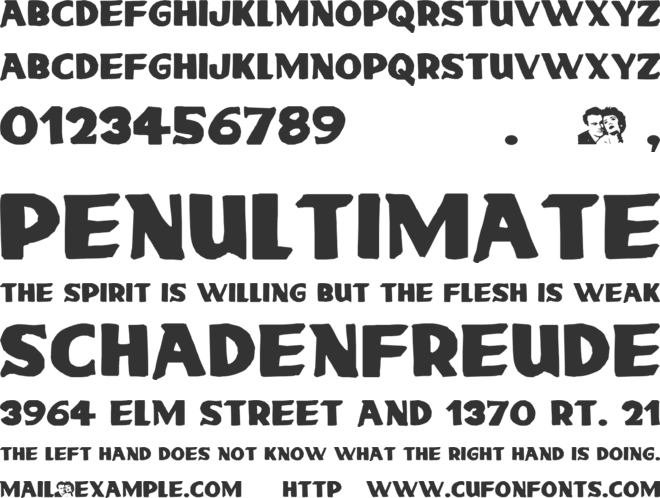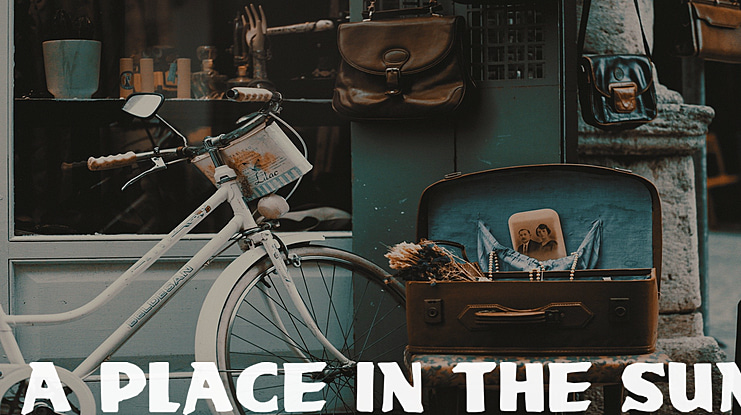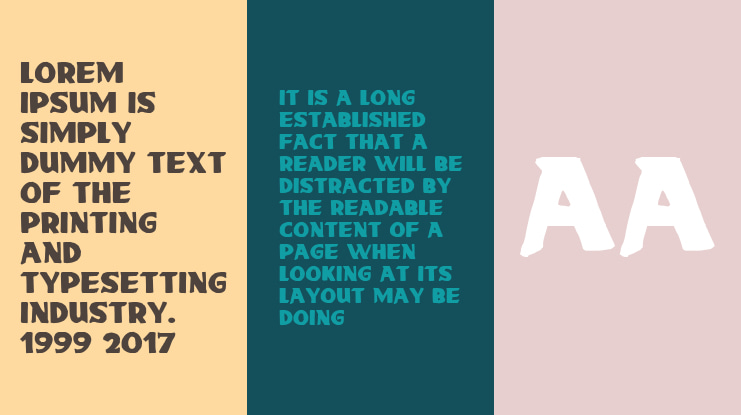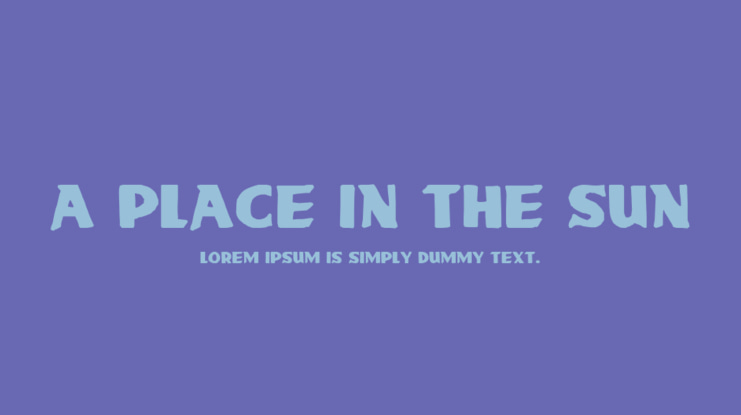
A place in the Sun Font
P.A.Vannucci
Direttamente dal film diretto da George Stevens e interpretato da Montgomery Clift e Liz Taylor, il font inedito per tutti gli estimatori del film.
Directly from the film directed by George Stevens and starring Montgomery Clift and Liz Taylor, the new font for all admirers of the film.